1. 圧倒的な読みやすさ、モダンな感性の本文用最強フォント「プリテンダード (Pretendard)」
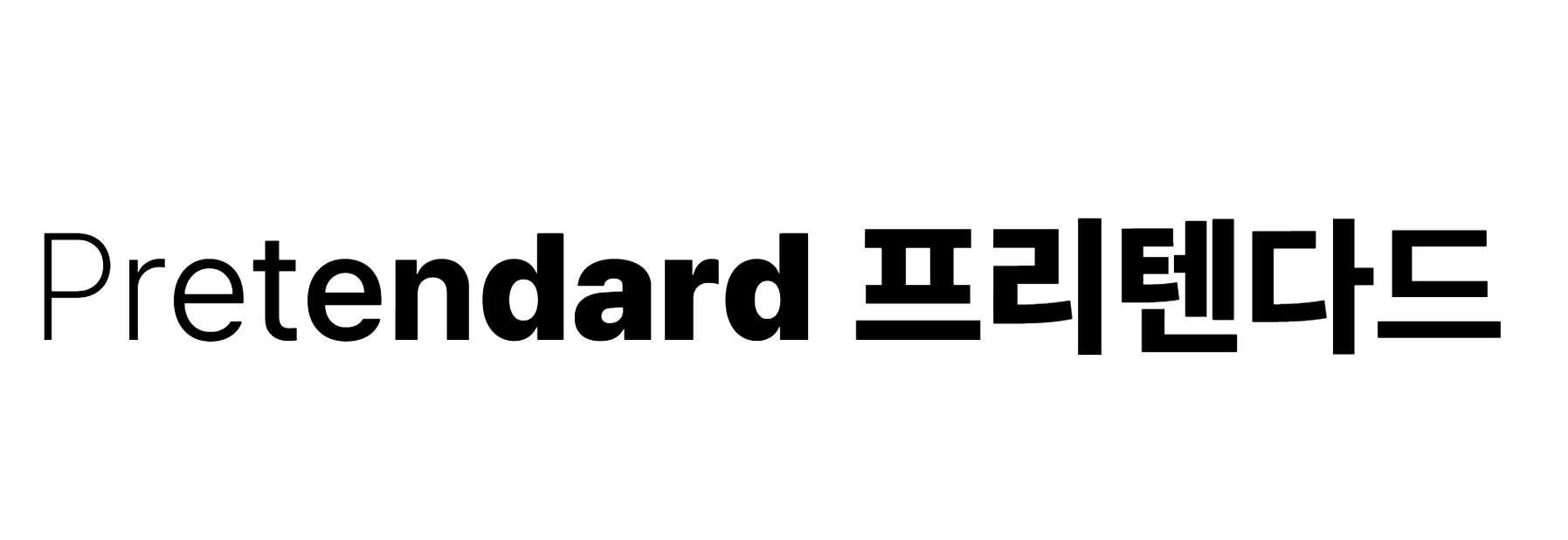
プリテンダードの特徴とおすすめカテゴリー(アパレル・ビューティー詳細ページの本文)
プリテンダードは、最近のWebデザインや詳細ページ制作で最も人気のあるフォントです。文字間隔や行間のバランスが非常に優れており、アパレルやビューティー関連の詳細ページにおけるスペック説明やブランドストーリーなど、文字数が多い本文エリアに一番おすすめのフォントです。
モバイル画面でも光る抜群の読みやすさ
スマートストアの購入者の80%以上がスマホで商品を見ていることを知っていましたか?プリテンダードは、高精細ディスプレイはもちろん、小さなスマホ画面でも文字がつぶれずハッキリと表示されます。本文テキストが読みやすくなることで、顧客の離脱を防ぎ、滞在時間を延ばす効果も期待できます。
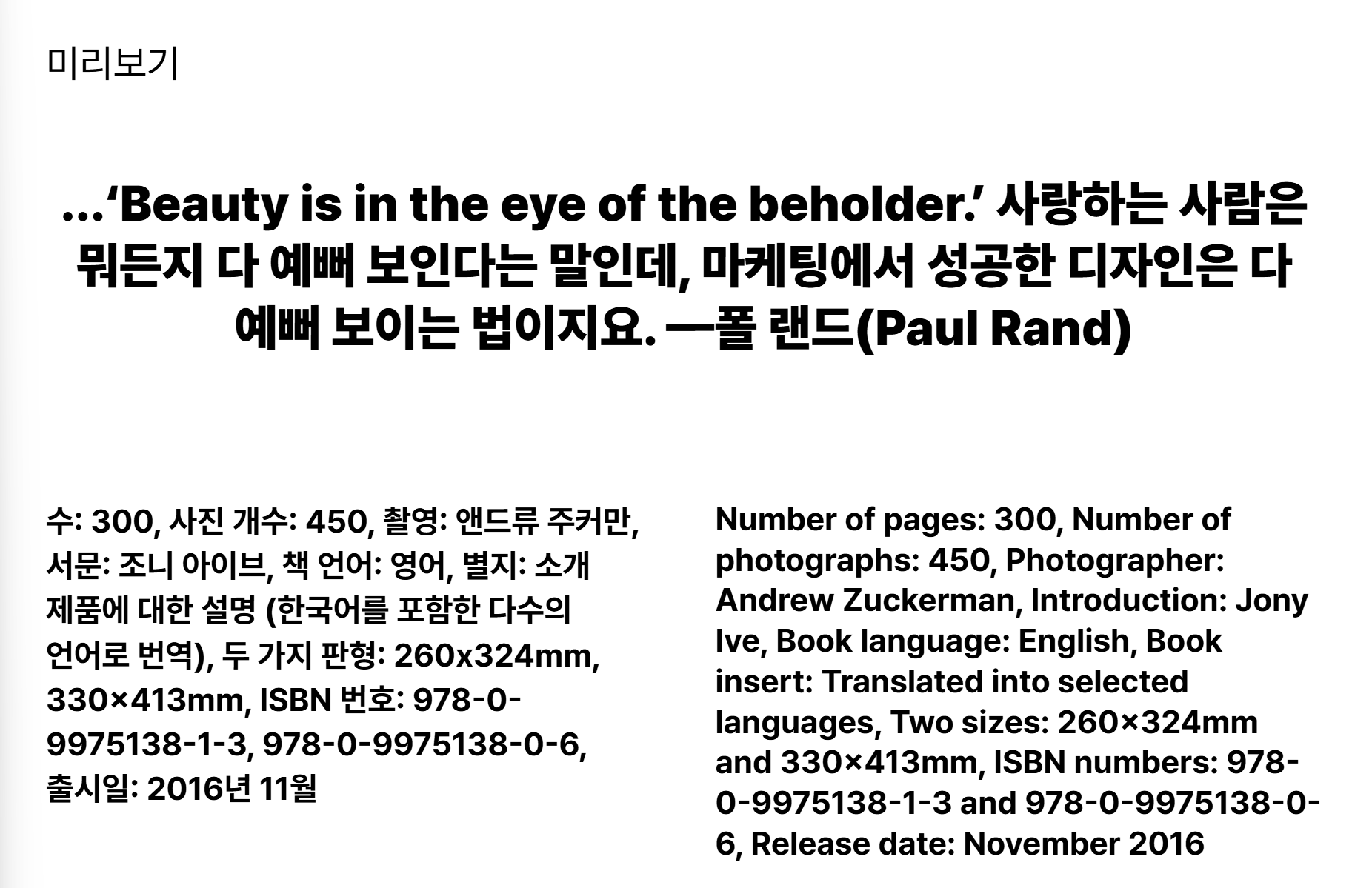
2. ギュッと詰まったスクエア構造が与える安定感とモダンさ「S-Core Dream (エスコア・ドリーム)」
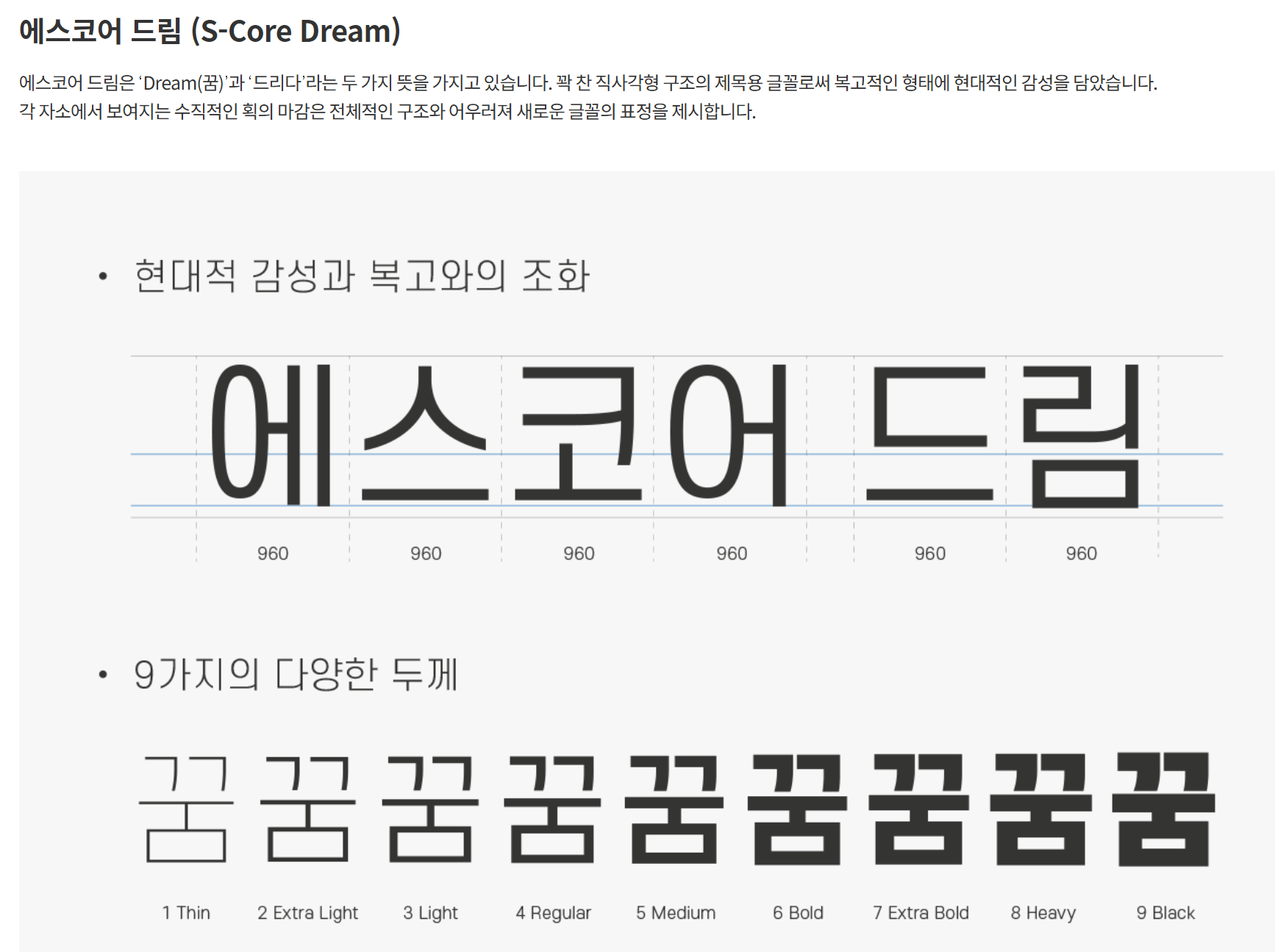
9段階の太さ(Thin~Black)で高い活用度
S-Core Dreamは、ギュッと詰まったスクエア構造が特徴のフォントで、非常にすっきりとした信頼感のある印象を与えます。特にThinからBlackまで計9段階の豊富な太さ(Weight)が用意されているため、このフォントファミリーだけでタイトルから本文まで統一感のあるレイアウトが作れます。
おしゃれな化粧品パッケージのようなタイトル作りのコツ
S-Core Dreamの細いウェイト(Thin, Light)は、洗練された落ち着きのあるビューティーブランドのロゴやパッケージのような雰囲気を出せます。逆に太いウェイト(Bold, Black)は、サムネイルでタイトルを目立たせたい時に最適です。
3. 可愛らしくて個性的なポイント使いに「Cafe24 Anemone (カフェ24 アネモネ)」
注目度を高めたいイベントバナーやサムネイルに推奨
詳細ページ全体を硬いフォントだけで埋めると、少し退屈に見えてしまうことがあります。そんな時「Cafe24 Anemone」を使うと、サムネイルやイベントバナーの注目度を一気に引き上げられます。柔らかい曲線とウィットに富んだ文字の形が、一瞬で目を引く効果を生みます。
若いターゲット層に刺さる、キッチュでトレンド感のある演出術
トレンドのストリートファッションブランドや個性あふれるインテリア雑貨ショップなら、アネモネフォント特有のキッチュな雰囲気を前面に出してみてください。堅苦しくなりすぎず、親しみがありつつも洗練されたポップアートスタイルのブランドムードを演出できます。
4. 温かみのあるナチュラルな手書き風フォント「Nanum筆ペン」
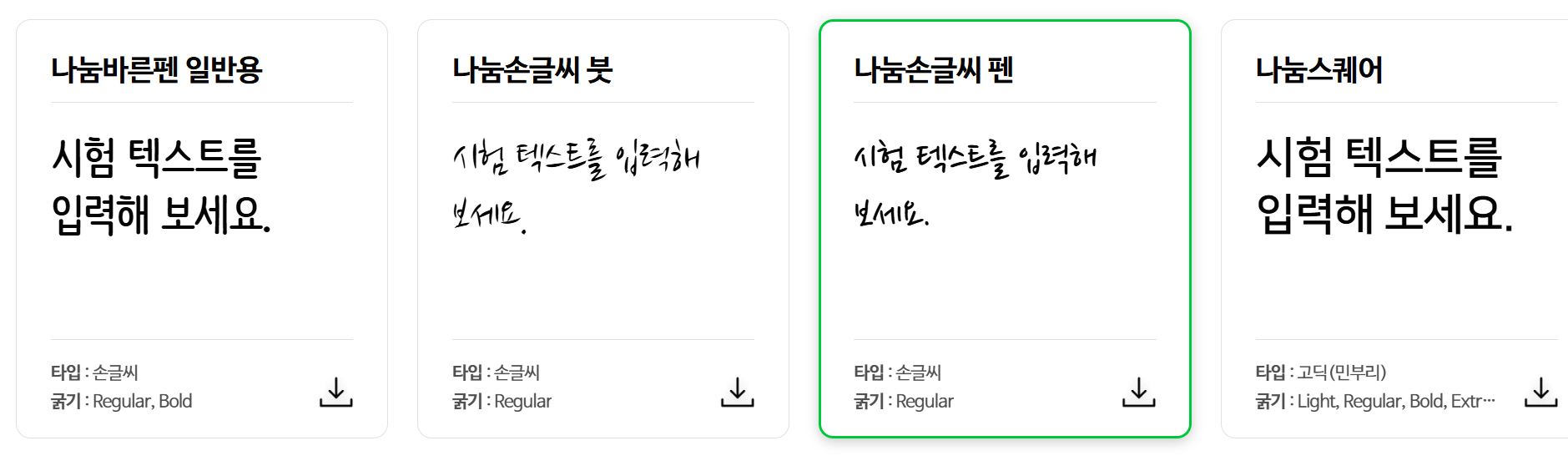
リビング/インテリア雑貨ショップに似合うエモーショナルなタッチ
自然派のウッド家具、エコなリビング雑貨、ハンドメイド製品などを販売しているなら、硬いゴシック体より人のぬくもりが感じられる手書きフォントがおすすめです。NAVERのNanum筆ペンは、自然な筆のタッチを活かしていて、リラックスした雰囲気を演出してくれます。
お客様レビューの強調や手紙のようなコンセプトに活用
詳細ページの途中に「店主からのメッセージ」を入れたり、実際のお客様のリアルな写真レビューの下に手書きフォントで一言添えるだけで、お客様からの信頼度がグッとアップします。ちょっとした感性が、お客様の心に響く瞬間を作ってくれます。
5. ショッピングモールやロゴに最適な洗練された「Godoフォント」
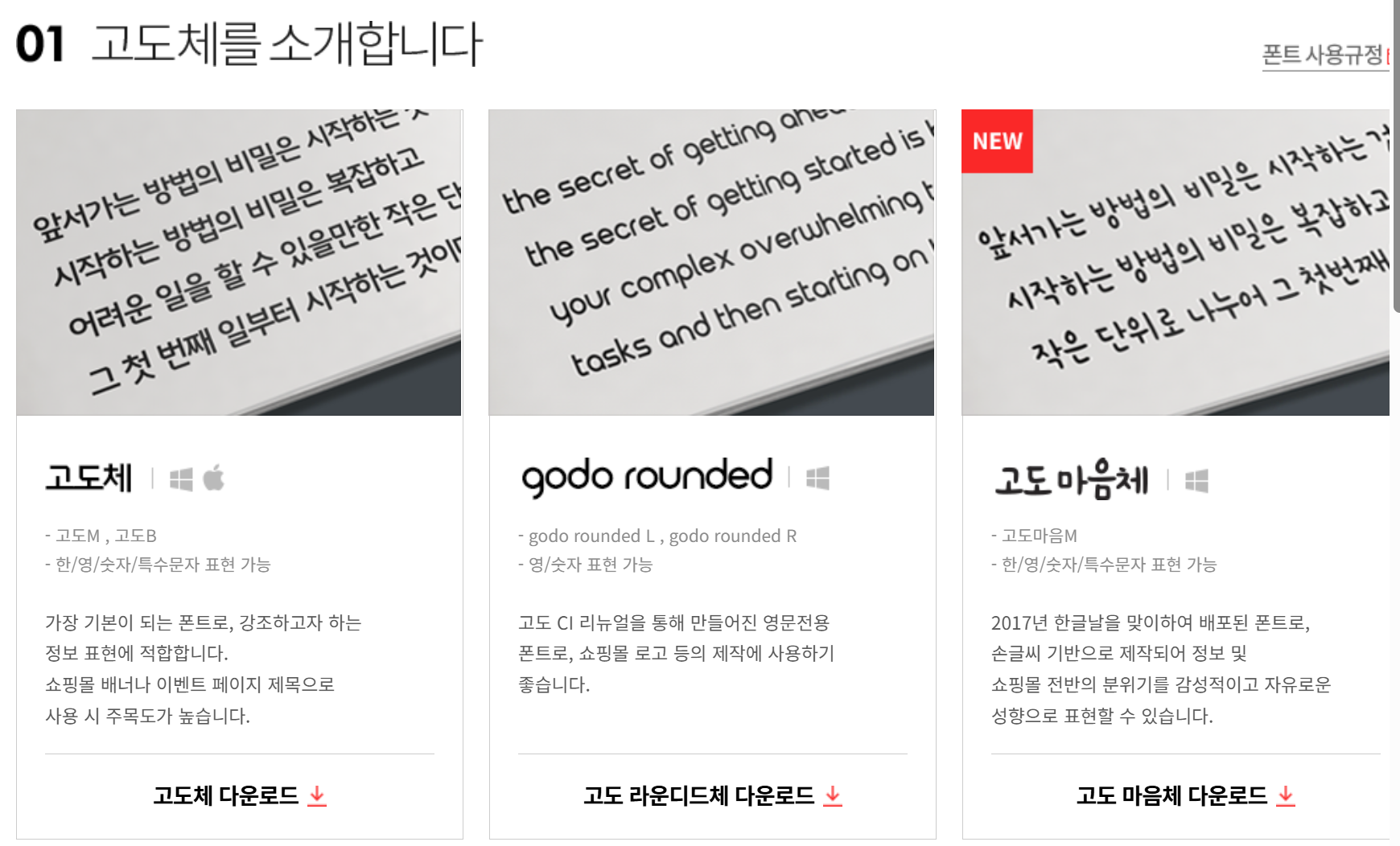
整いながらも個性が光る「Godoマウム体」と「Godoラウンド体」
ショッピングモールソリューションのNHN Godoから配布されている「Godoフォント」は、Eコマースサイトに最適化されています。まっすぐで綺麗な線の中に丸みを帯びた処理が施されており、知的でありながらも親しみやすい雰囲気が特徴です。
ファッションブランドのアイデンティティを生かす英字と韓国語の調和
Godoフォントは、韓国語だけでなく英語フォントとのビジュアルバランスが非常に優れています。ファッション詳細ページのトップに載せる英語のサブタイトルやロゴを作る際、別の英語フォントを組み合わせなくても、スタイリッシュなムードが自然に演出できます。
6. テクニカルで整った印象の「Spoqa Han Sans」
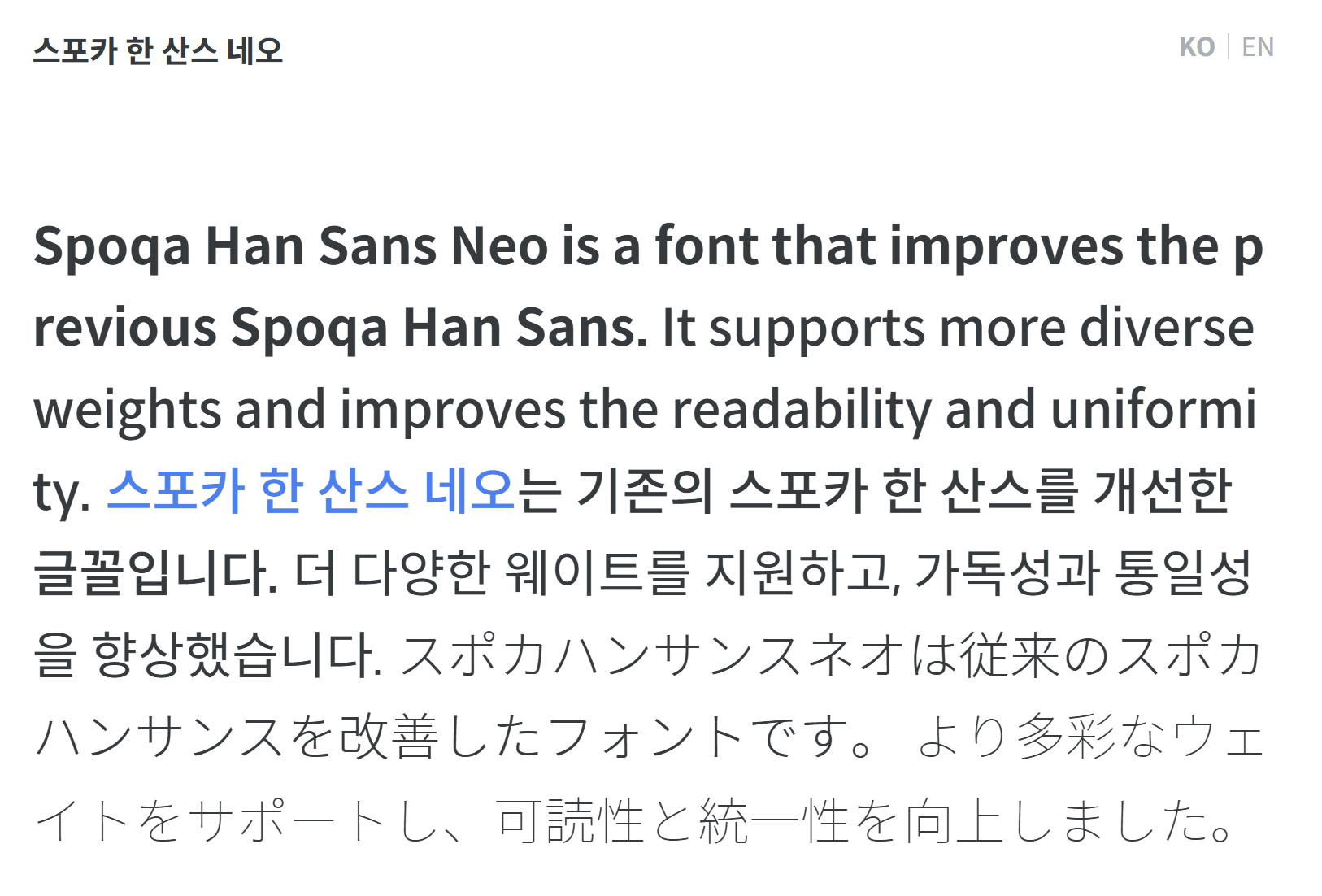
数字が多い価格表やサイズ表におすすめの理由
Spoqa Han Sansは、もともとUIデザイナーの間で広く愛されているフォントです。このフォントは韓国語だけでなく、「数字」の文字間隔や太さのバランスが最高レベルにチューニングされています。
- おすすめの活用ポイント:詳細ページ下部の製品規格表、実寸サイズ表、数量別価格割引表などに使うと、数字の可読性が最大化され、情報が伝わりやすくなります。
グローバルWebフォント基準に合わせた、崩れのない可読性
Webブラウザの種類や、Android、iPhoneといったOSに関係なく、文字化けが全く発生しない精巧さを誇ります。正確で綺麗な情報伝達が必須の電子機器、精密家具、健康食品などの詳細ページデザインに積極的に推奨します。
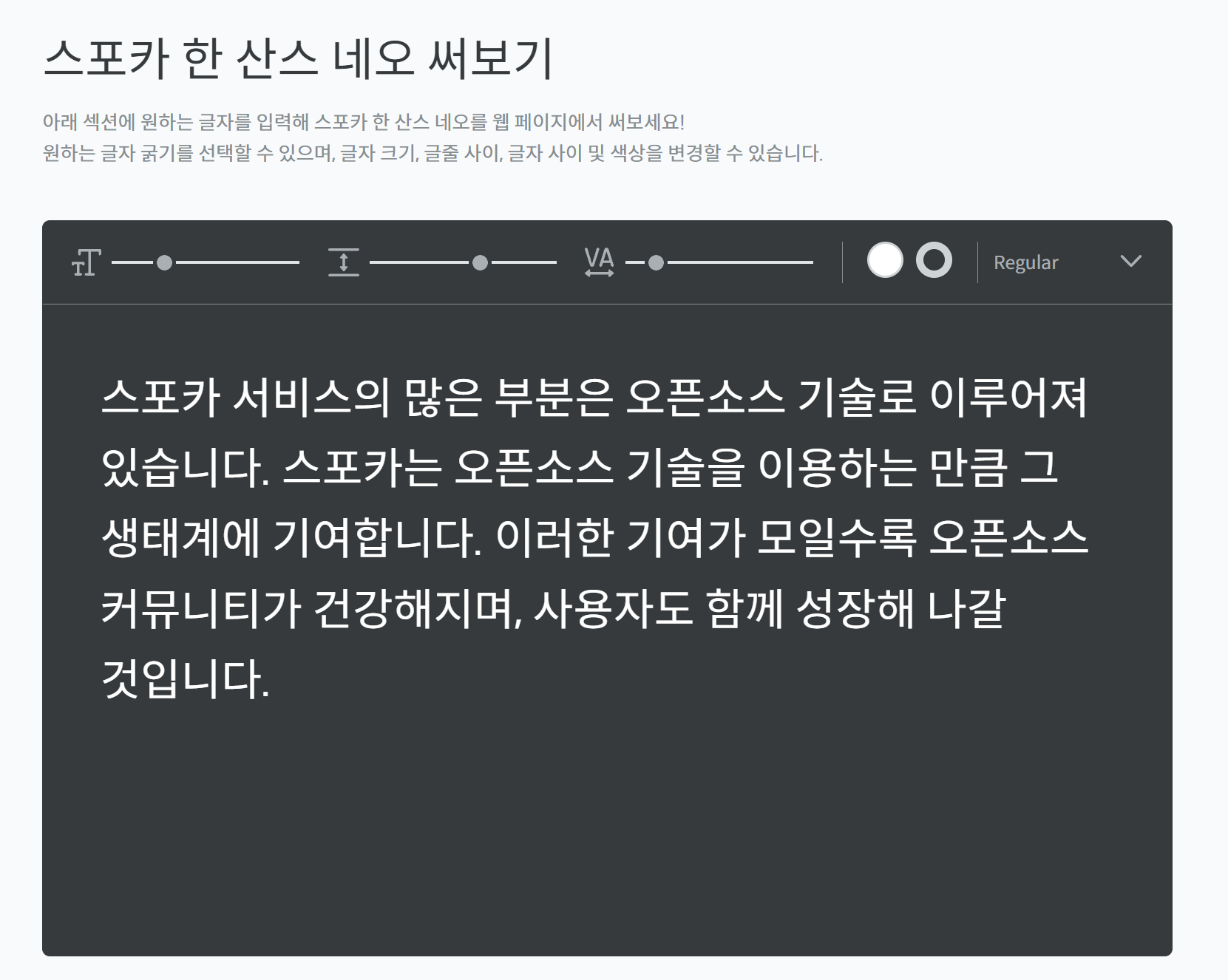
7. 落ち着きのある高級な雑誌レイアウト感「Ridiバタン(明朝体)」
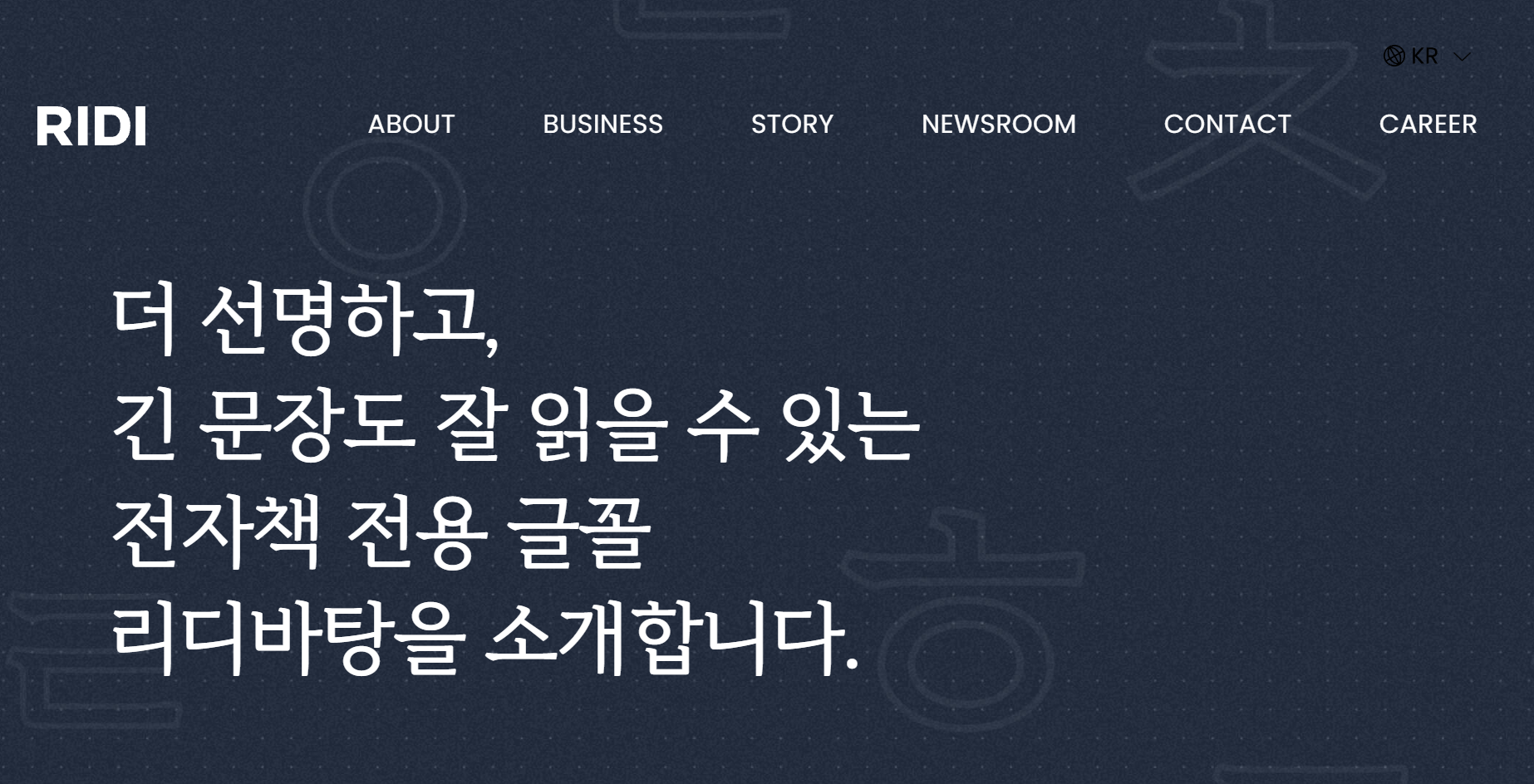
明朝体系のフォントが醸し出すクラシックでエレガントな雰囲気
モダンなゴシック体ばかりの市場で差別化を図りたいなら、品格ある明朝体である「Ridiバタン」に注目してみてください。電子書籍プラットフォーム「RIDI」が画面での読みやすさを追求して作り上げた明朝体で、一般的なフォントに比べて柔らかくも重厚な力強さを持っています。
ビューティーブランドのストーリーやブランド哲学を紹介するエリアに最適
高級オーガニック美容液、プレミアムディフューザーなど、ハイエンドなムードを目指すブランドなら、Ridiバタンのフォントを大きく配置してみてください。高級雑誌(Magazine)の一ページを読んでいるような、クラシックで魅惑的なレイアウトがとても簡単に完成します。
| フォント名 | 主なスタイル | 読みやすさ/目を引く度 | おすすめのショップジャンル | おすすめの使用箇所 |
| Pretendard(プリテンダード) | モダンゴシック | 最高(スマホ最適化) | ファッション、ビューティー全般 | 詳細ページの案内文、本文全体 |
| S-Core Dream | 直線的なゴシック | 高(幾何学的な安定感) | ミニマルなライフスタイル、クリーンビューティー | サムネイルのタイトル、パッケージデザイン |
| Cafe24 Anemone | カジュアル系 | 高(個性あふれる) | ヤング層向けファッション、雑貨 | セールバナー、新着アイテムのお知らせ |